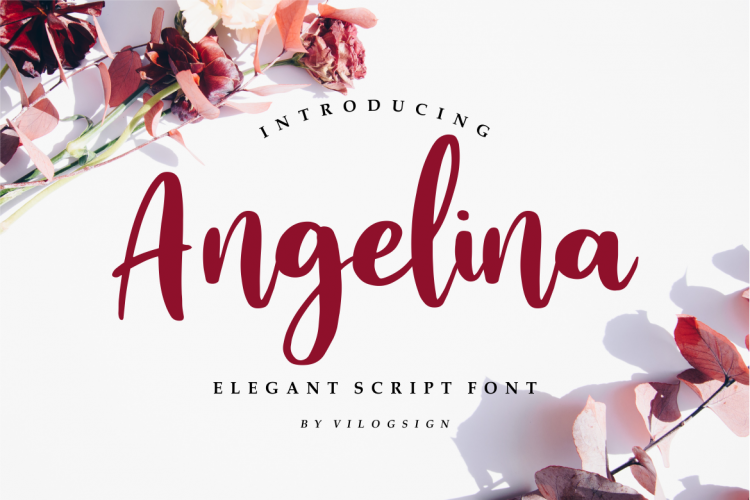
Angelina Playful Script Font – Download Grátis
Esta é uma fonte tipo script com curvas naturais e linhas suaves. Introduzimos a Fonte Angelina. Com toques naturais, ela torna esta fonte incrivelmente bonita e adorável. Esta font tem todos os alternativos de minúsculas, então você pode escolher o melhor para suas necessidades. Aconselhamos fortemente este tipo de fonte para criação de logotipos, frases, revistas, moda, marcação e muito mais. A font Angelina é perfeita para aqueles que querem dar vida a seus projetos com um toque leve e elegante. Descubra o encanto da font Angelina Playful Script para seu próximo projeto visual.